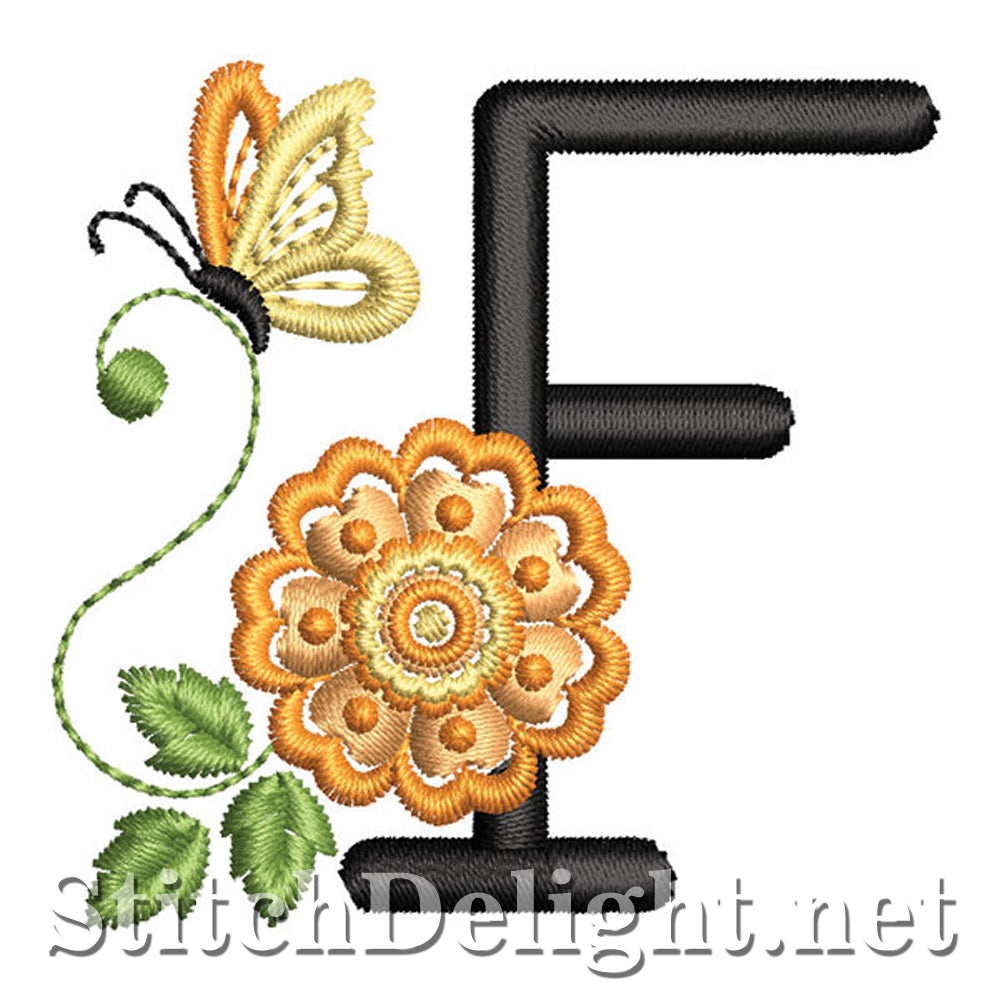
Personnalisez votre projet avec cet ensemble de monogrammes élégants avec de magnifiques fleurs et papillons au coucher du soleil - Version BX pour le logiciel Embrilliance inclus dans l'achat de la police COMPLÈTE uniquement, pas pour les lettres simples - La hauteur des lettres est de 2,1 pouces / 55 mm